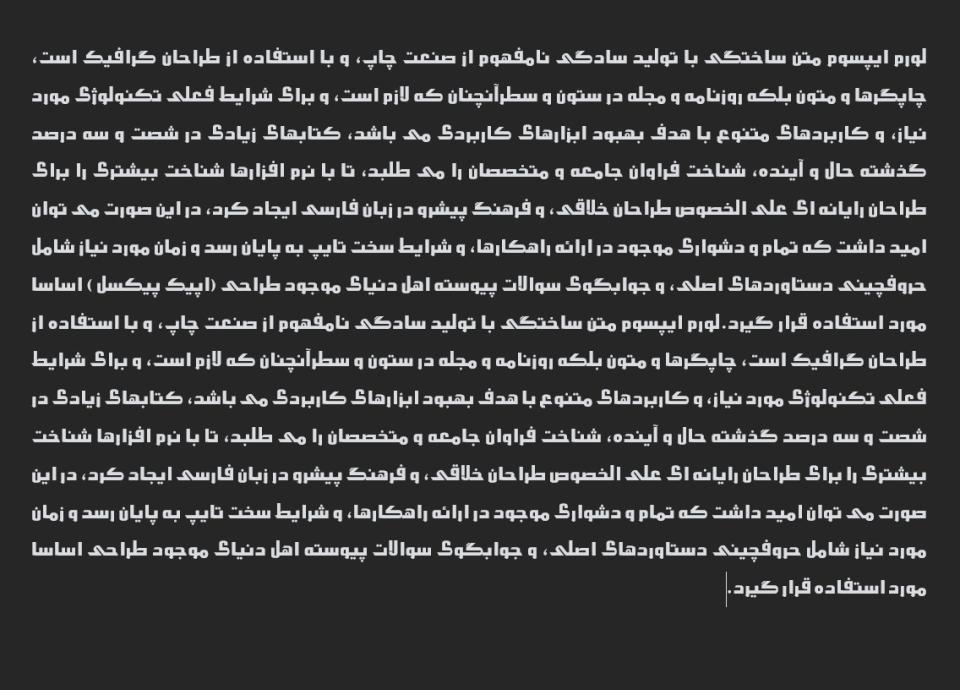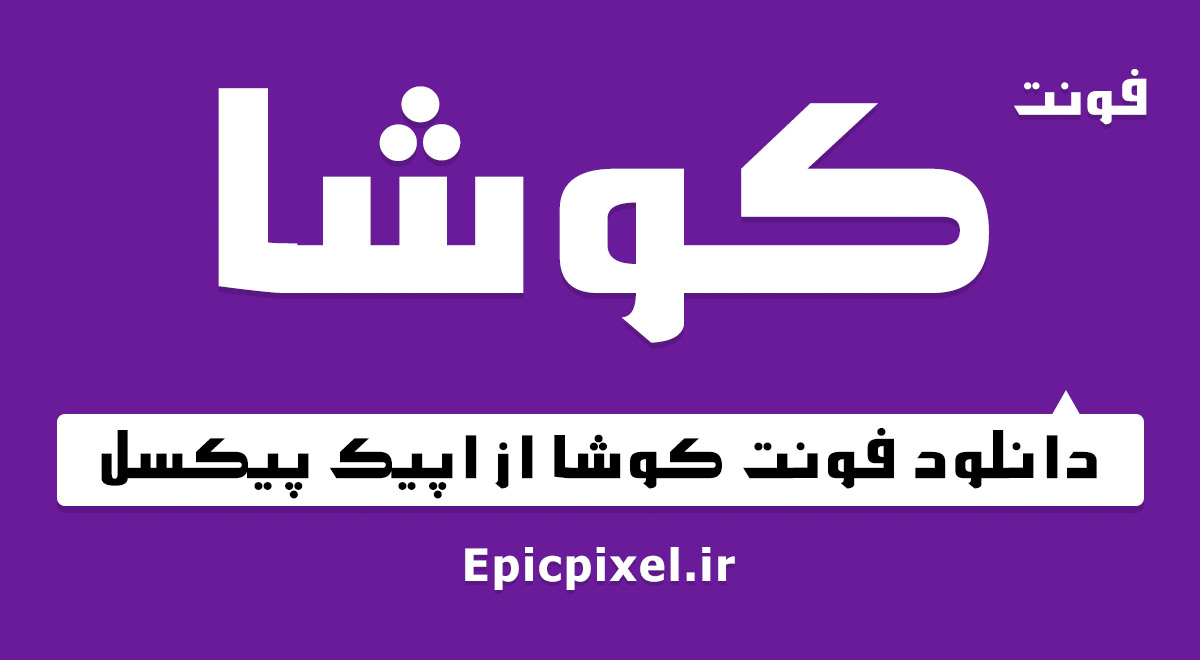
فونت کوشا فارسی
فونت کوشا فارسی، انتخابی ایده آل برای طراحانی است که به دنبال ظرافت و خوانایی در آثار خود هستند. این فونت با طراحی منحصر به فرد خود، ترکیبی چشم نواز از خطوط نرم و ساختار هندسی ارائه می دهد که هم در متن های طولانی و هم در عناوین کوتاه، به خوبی خود را نشان می دهد.
ویژگی برجسته کوشا، خوانایی بالای آن در اندازه های مختلف است. این ویژگی به طراحان اطمینان می دهد که متن هایشان در هر اندازه ای، از کارت ویزیت گرفته تا بنرهای بزرگ، به راحتی قابل خواندن باشد. همچنین، طراحی مدرن و در عین حال کلاسیک کوشا، آن را برای طیف وسیعی از پروژه ها، از طراحی وب سایت و اپلیکیشن گرفته تا طراحی جلد کتاب و پوستر، مناسب می سازد.
اگر به دنبال فونتی هستید که به طرح هایتان جلوه ای خاص و حرفه ای ببخشد و در عین حال خوانایی متن را تضمین کند، فونت کوشا فارسی گزینه ای بی نظیر است. این فونت به صورت رایگان در دسترس شماست و می توانید با دانلود آن، تحولی چشمگیر در طراحی های خود ایجاد کنید.